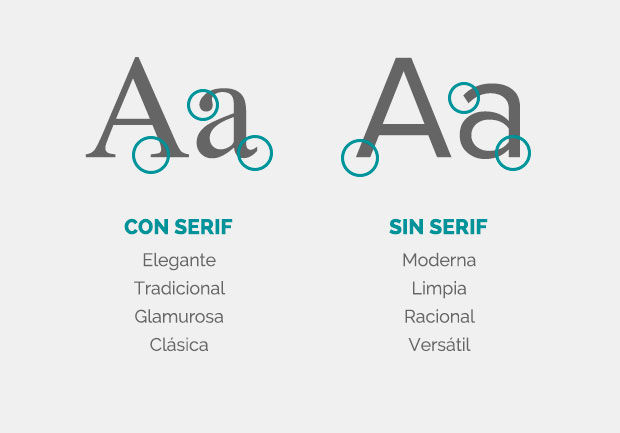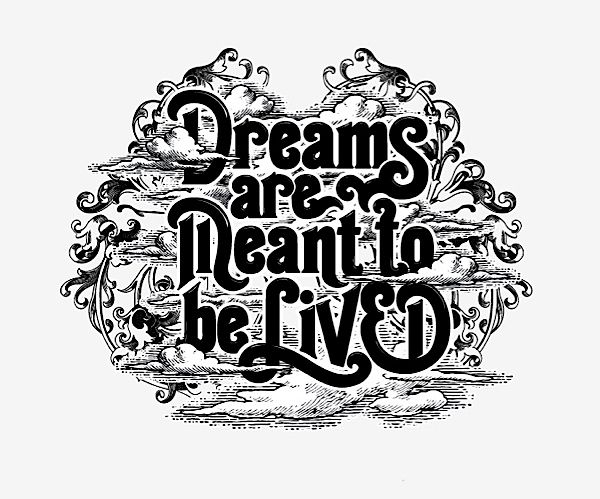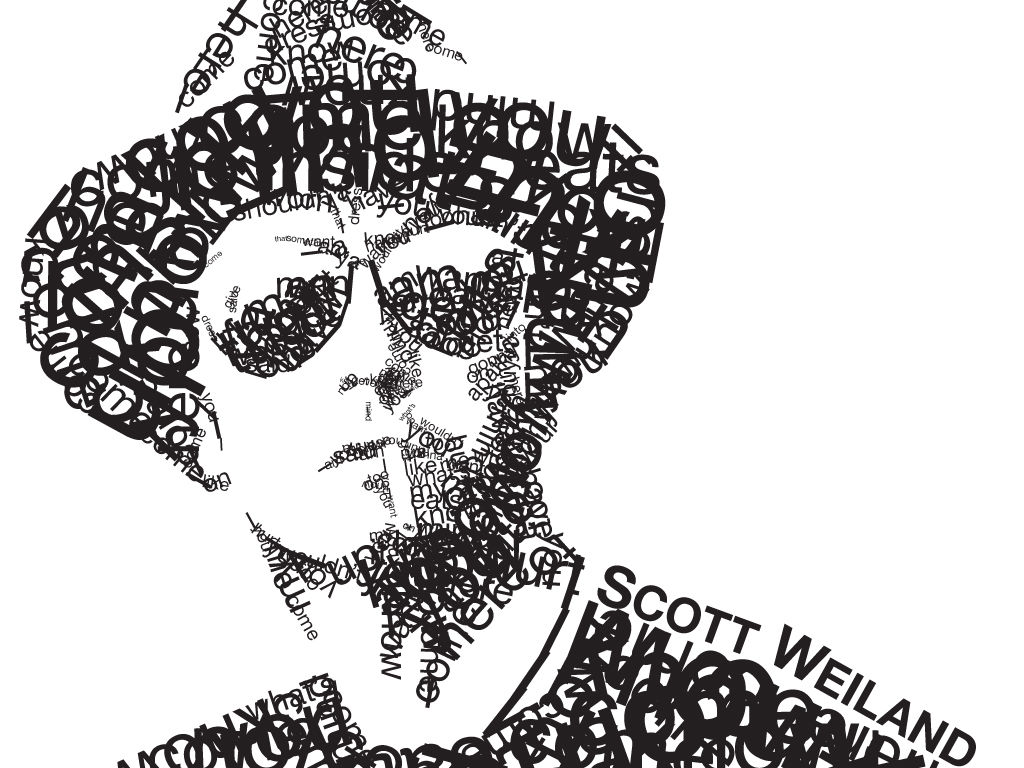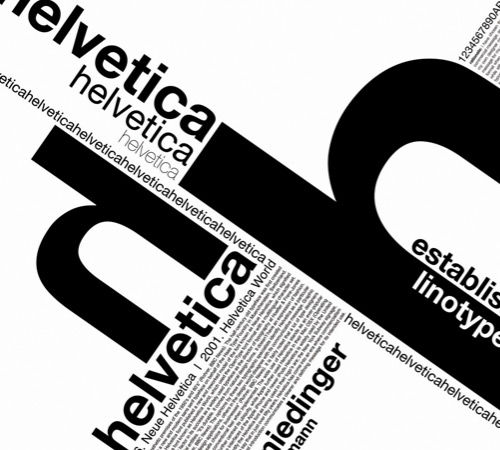
Tipografía
Tipografia y sus conceptos
Tipografía
1. Es el arte de diseñar letras y componer textos de tal modo que pueden leerse de un modo fácil , eficaz y agradable
1. Grupos fundamentales de la tipografia: *Tipografias con Serif *Tipografia sans
2. Estructura de la letra: Es esa señal que se transfiere , pinta o esculpe y viene a ser la unidad fundamental del lenguaje escrito y puede presentarse en : Capitales, minusculas , numeros, versalitas , ligadura so simbolos
1. Partes de una letra
1. Pautas de la letra: 1.Linea superior de letras de rasgo anscendente. 2.Linea superior de altura X. 3.Linea inferior de altura X. 4.Linea inferior de letras de rasgos descendentes
2. Fuente tipográfica: Es la que se define como estilo o apariencia de un grupo completo de caracteres , números y signos regidos por unas características comunes.
1. Medidas tipográficas: *Letra: *Tamaño de la letra *Linea: *Interlinea *Profundidad *Justificación *
1. Disposicion del texto: Derecha, Izquierda, Centro , Justificado